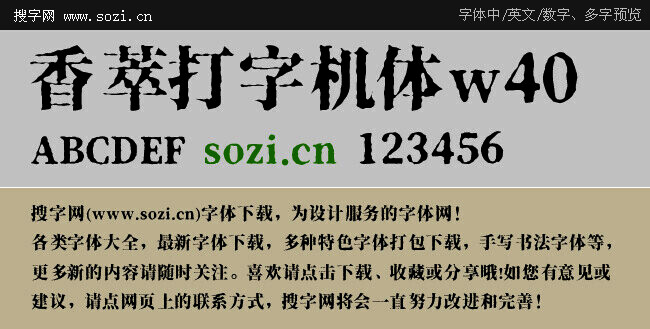
香萃打字机体w40
搜字网提供一款香萃打字机体w40中文艺术字体下载,香萃打字机体是一款笔画模仿打字机洇墨效果的宋体字,包含3个字重。区别在于汉字横画粗细、细节的粘连程度,以及英文字母衬线的不同。字体的原型是开源项目思源宋体。 这款字体允许个人或企业自由传播、分享,免费商用。字体包含两个字重。适合包装设计、海报设计、广告设计等应用。